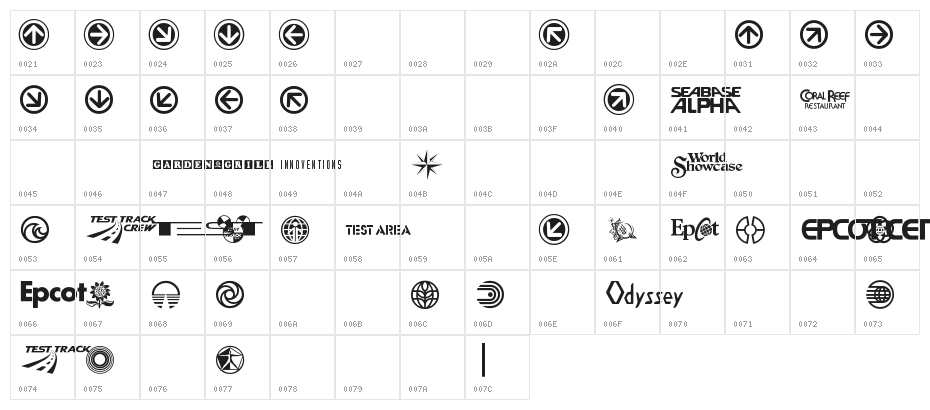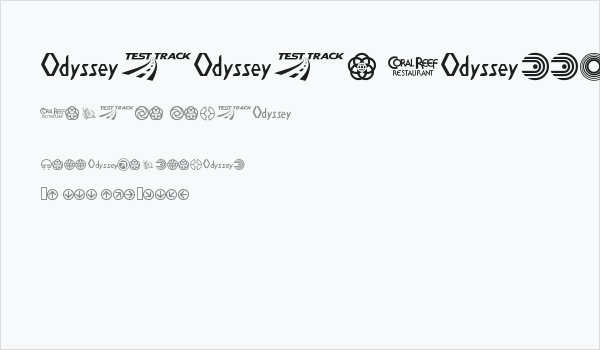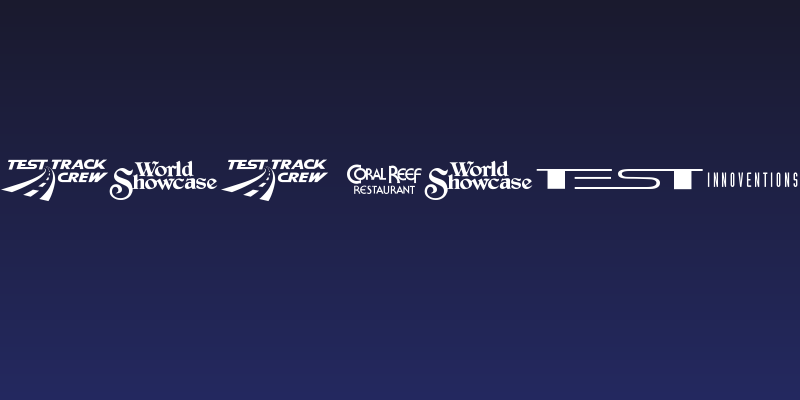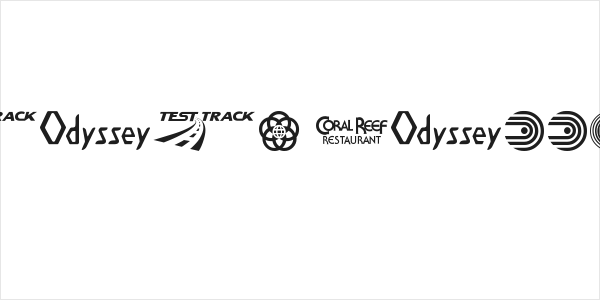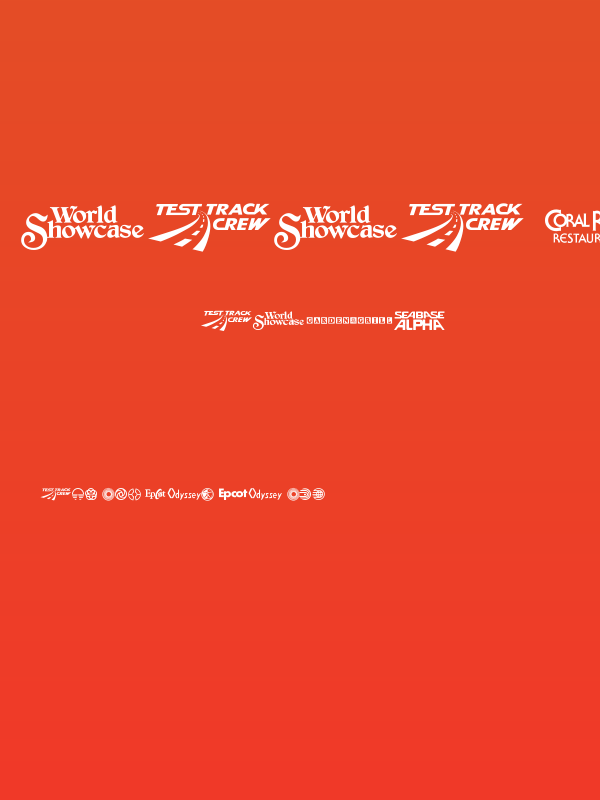
Prototype Community Font
| Область применения | Headlines, Digital displays, Signage |
| Рекомендуемые проекты | Ideal for digital interfaces, signage, and projects requiring high readability and a modern look. |